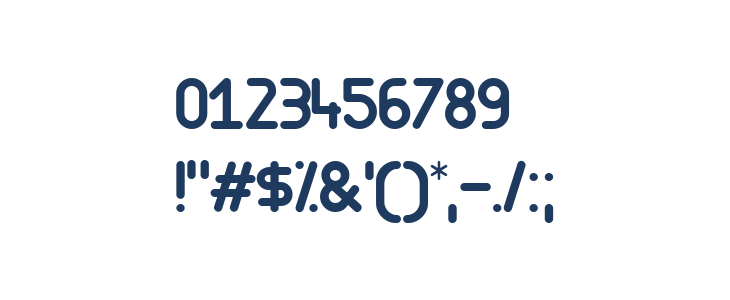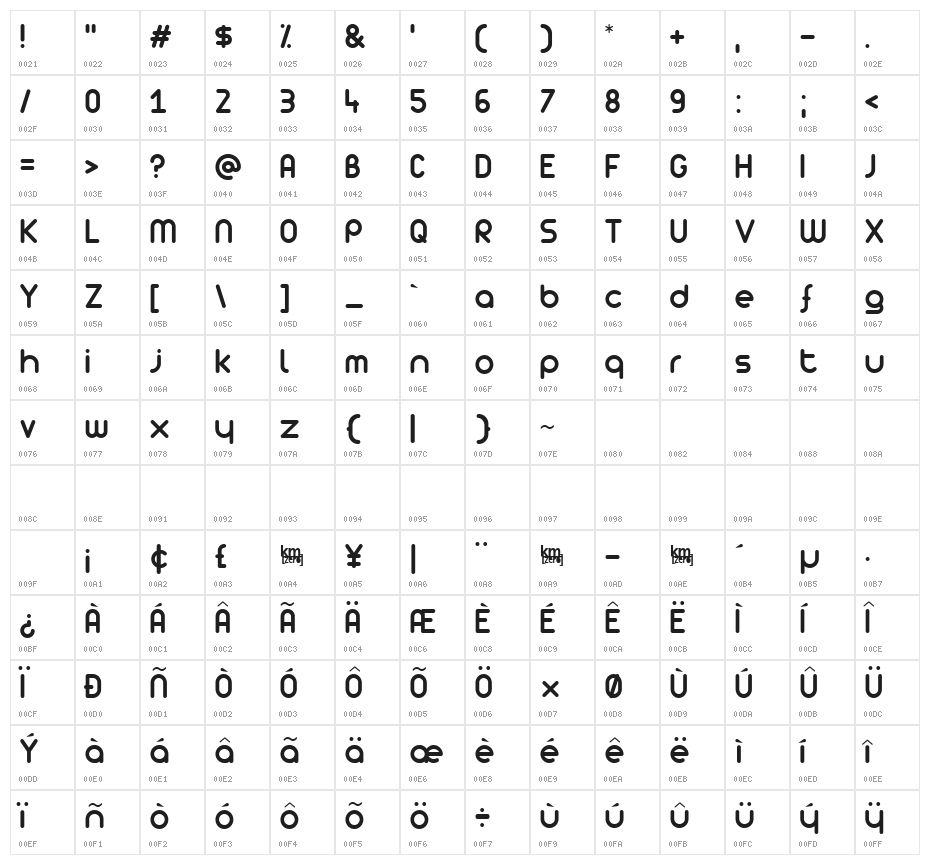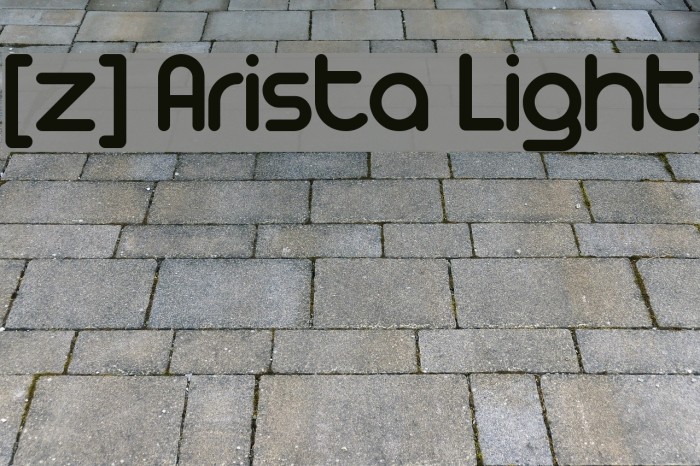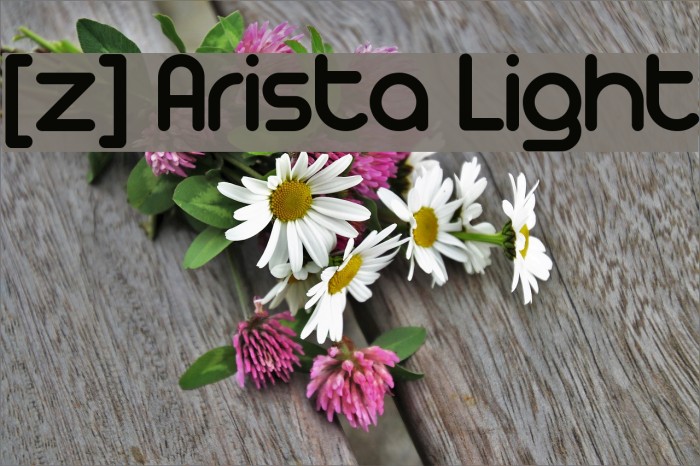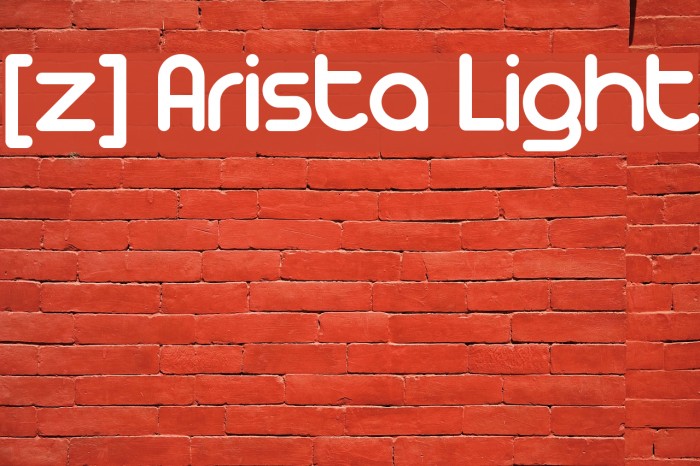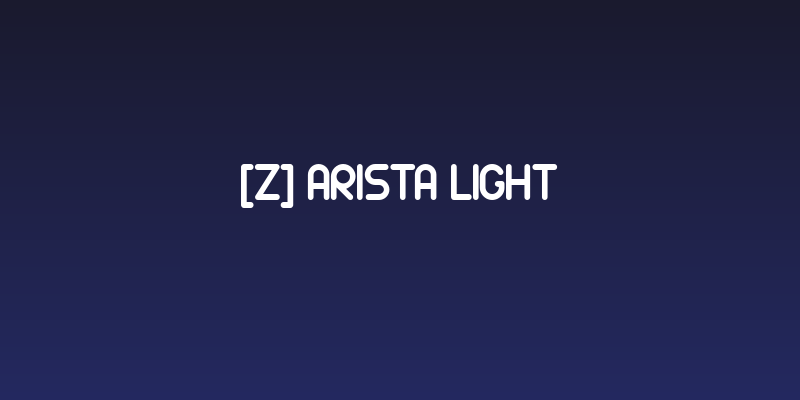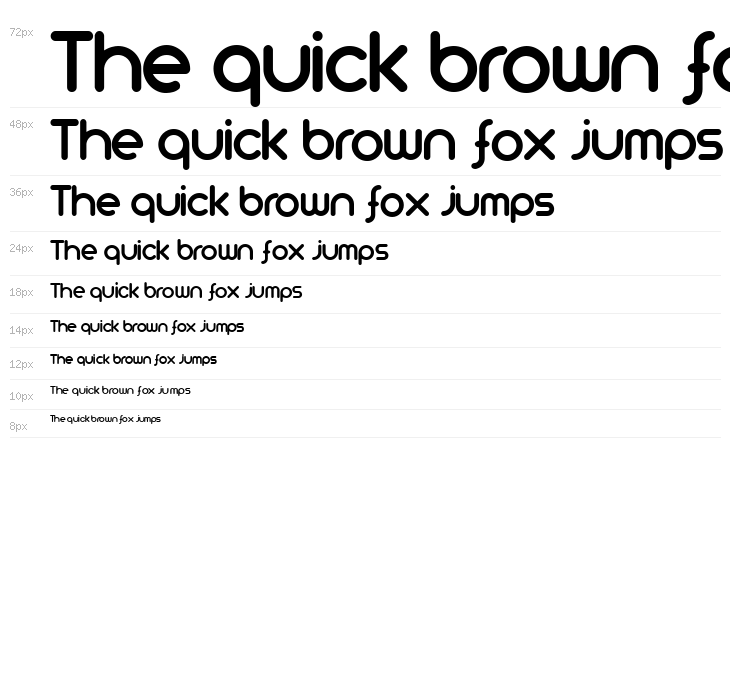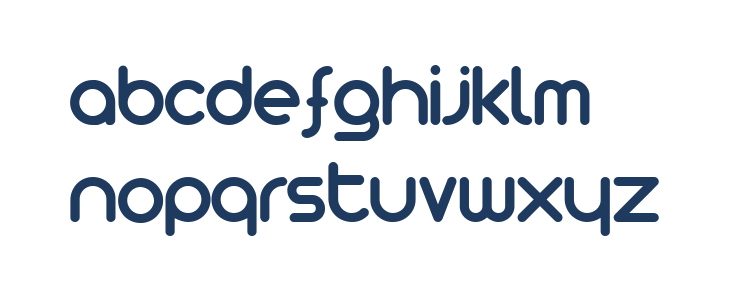
[z] Arista Light Font
| Progetti proposti | Ideal for branding, advertising, web design, and user interfaces where a modern and approachable look is desired. |